文字是一种记录与传达语言的符号,而随着图形化时代的来临,文字与图形的关系在设计领域起着举足轻重的作用。
文字经过艺术化设计后,可以让文字形象变得情景明确、视觉突出,从而强化语言效果。在工作中或是生活中,能够自己设计字体,无论是提升页面品质,还是展现自己独一无二的审美情趣,表达自己心中意愿,都是有积极作用的。
经过艺术化设计以后的文字,便成为更具有自身特色的视觉符号。面对一个将要设计的字体,我们首先要做一个充满想象力构造计划,再利用代替、共用、叠加、尖角、曲线、图型、字体连接、随意手写等方法转换字体。
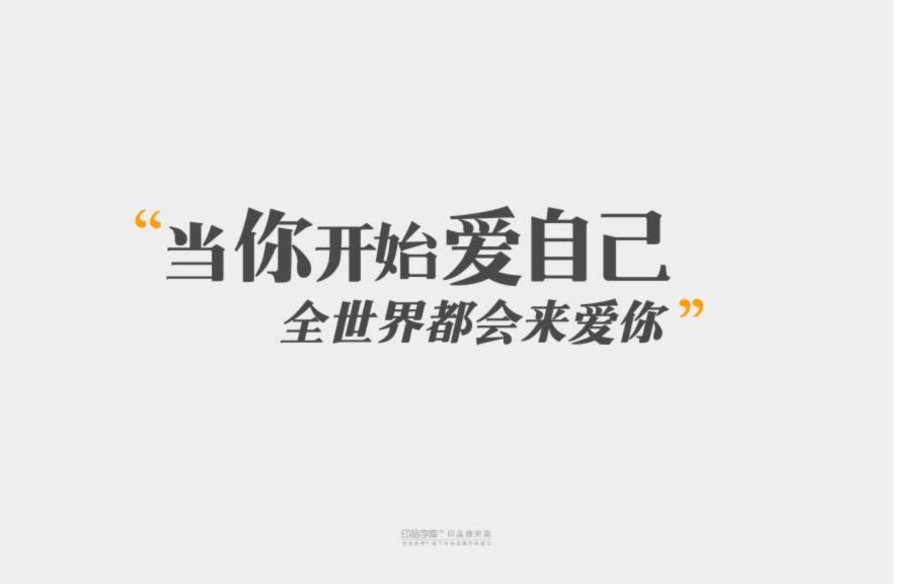
不过字体不能脱离主题,我们可以根据其特点来区分:
一、力道、坚实、厚重、硬朗……这类字体气势突出,视觉冲击力明显,个性张扬有力,能给人视觉上的震撼。 这类字形在表现刺激,战争类、灾难类电影海报中,这类字形比较常见。同时冒险的情景时也比较常用,如体育活动、极限运动的主题。
二、柔美、纤细、优雅、飘逸 …… 这类字体适合表现细腻情感,如女性设计主题、情感类设计主题、公益类设计主题等等,通过柔美的曲线,形成人与字的情感共鸣,以达到最佳效果。
在选定字体的风格趋势后,就需要给字体做相应的视觉调整。例如:笔划之间的距离、字形的倾斜角度、特殊地方做圆角处理等等。使字体始终有一个贯穿的规则在里头,这样才能整体协调。
最后我们要记得,在设计过程中应该尽可能地保证文字的可阅读性。不能把一个汉字画到难以辨识,这就是喧宾夺主了。当练习字体设计时,找有代表性的字体来做,练习有代表性的字体不但可以激发你的创意,还可以提高你的思维能力。
设计属于自己的字体,做独一无二的你。